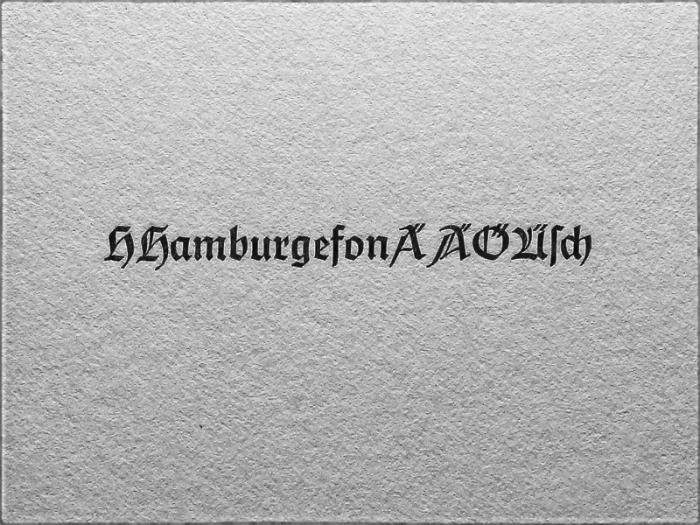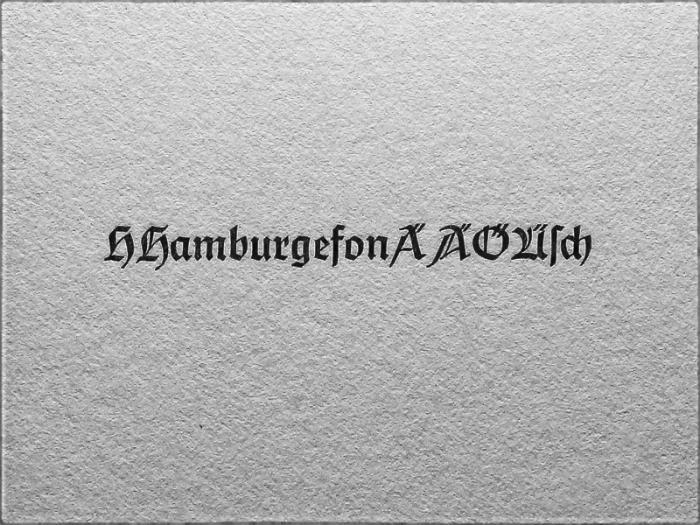
Kann mir jemand mit der Identifizierung dieser Schrift helfen? Ich habe sie in 12p Bleisatz vor etwa 10 Jahren in meine Werkstatt übernommen aus einer Setzerei-Auflösung, gußfrisch, aber ohne Namensschild. Sie ist mit Zierversalien ausgestattet. Weiß jemand, wie sie heißt?
Wieder einmal allerbesten Dank! Ich hatte die Post-Fraktur im Kapr schon vor Augen, aber sie hat in der betrachteten Ansicht deutliche Unterschiede. Im Kandler hätte ich nachschauen sollen. Die Schrift im Kapr ist wohl die digitale Version, die auch Judith Schalansky ohne Zierversalien zeigt und die vom Bleisatz doch deutlich abweicht. Deshalb dachte ich, es wäre eine andere, die ich nicht kenne. Die Digitalisierung halte ich für schlechter als die Bleisatzvariante, den verkürzten Auslauf des g, das offenere H, das breitere r – und die Zierversalien sind neu gezeichnet. Darf ich fragen, was Sie von der digitalen Interpretation halten? Und hätte man sie nicht anders nennen sollen?
Wenn die Digitalisierung so deutlich abweicht, könnte man mir eine große Freude machen, und mir eine möglichst hoch auflösende Abbildung aller Figuren zukommen lassen. Ich würde sie nämlich gern so originalgetreu wie möglich digitalisieren. Gerne auch eine Ablichtung der Lettern, da ich dann auch den Kegel sehe, und dies komplett in die Font-Metrik übernehmen könnte.
Ich hab die Schrift nur in Cicero, also 12p. Für eine Digitalisierung müßte man auch die großen Grade berücksichtigen und eine Mischung aus allem herstellen, nicht wahr? Mir fehlt die Zeit für solche Arbeiten, also alles setzen und Reproabzüge machen, das dauert ja mindestens zwei Stunden. Es müßte in Bibliotheken Kataloge der Schrift geben.
Ach, Herr Reichardt, noch eine Nachfrage: Kapr gibt 1937 und die Gießerei Stempel an, Sie nennen Berthold. Würden Sie da noch mal nachschauen?
fraktur.de sagt: Die Entstehung der Post-Fraktur, wie die Schrift später im Handel hieß, zog sich über mehrere Jahre hin und war von einigen Rückschlägen überschattet. Erst als die Schrift 1937 von der Gießerei Berthold übernommen wurde, kam es zu einem zügigen Ausbau der weiteren Grade (6-48p).
und weiter:
Entworfen von Herbert Post (1903-01-13 Mannheim bis 1978-07-09 Baiersoien) in den Jahren 1933 bis 1935
gestochen von Paul Koch
hergestellt von der Schriftgießerei Bauer in Frankfurt
übernommen von Berthold in Berlin und dort ausgebaut und vervollständigt.
Ab 1940 entstanden die Zierversalien Mager und Halbfett.
Über die bewegte Entstehungsgeschichte gibt der Katalog zur Ausstellung über das Schaffen von Herbert Post Auskunft: ISBN 3-930195-22-4 (Halle 1997), darin der Aufsatz von Katja Schneider: „Die Schriften von Herbert Post“ (Seiten 61 bis 90, mit zahlreichen Abbildungen).
Markwart Lindenthal hatte den mageren Schnitt von Gerhard Helzel erworben und benutzt ihn für die täglichen Briefe. In Ermangelung der Auszeichnungsschriften hat er mit seiner Söhne Unterstützung diese Ergänzungen selbst vektorisiert und damit die Schriftenfamilie vervollständigt.
(Post-Fraktur für die täglichen Briefe – das ist drollig. Wenn sie gut gemacht sind, bekommt der Postempfänger eine Urkunde, und wenn sie mit den langen WORD-Voreinstellungszeilen geschrieben sind, einen Haschmich.)
Ich hab die Schrift nur in Cicero, also 12p. Für eine Digitalisierung müßte man auch die großen Grade berücksichtigen und eine Mischung aus allem herstellen, nicht wahr? Mir fehlt die Zeit für solche Arbeiten, also alles setzen und Reproabzüge machen, das dauert ja mindestens zwei Stunden. Es müßte in Bibliotheken Kataloge der Schrift geben.
Wenn ich dann ein gutes Foto von allen Figuren in hoher Auflösung hätte (vielleicht mal ausprobieren, die Lettern auf den Scanner zu stellen), hhätte das allerdings auch den Vorteil, dass man dann die Schrift in der Test-Entwurfsgröße digitalisieren würde. Viele Digitalisierungen kranken ja gerade daran, das es praktisch nur die Display-Größe gibt, weil hier nach einer großen Schriftgröße digitalisiert wird, und das, weil die Abdrucke, die zur Vorlage dienen, einfach bei großen Schriftschnitten sauberer sind. Direkt von den Lettern bekäme man damit vielleich auch eine gute Textschrift, die sich dann mit der anderen Digitalisierung gut kombinieren ließe.
Es tut mir wirklich leid, mir fehlt die Zeit dafür. Ich könnte so etwas nur als Auftrag gegen Rechnung übernehmen, aber nicht kostenlos, das dauert einfach zu lange. Und ich habe auch keinen Scanner. Ist es nicht ohnehin sinnvoller, nach den Originalzeichnungen und Probegüssen zu forschen? Denn auch für den Bleisatz mußten Schriftschöpfer Kompromisse eingehen. Oder soll ich den Stezkasten fotografieren? Die Schrift ist stehend untergebracht, zufällig. Aber auch das kostet ein halbes Stündchen. Stativ, Langzeitbelichtung, Ausleuchtung. Das halbe Stündchen habe ich dieses Jahr nicht mehr. Im April vielleicht. Oder du kommst vorbei oder schickst jemanden, der ein Foto machen kann.
Nach den Originalzeichnungen zu digitalisieren ist natürlich in einer Richtung ideal - das gint dann einen super exakten Font, der allerdings dann zumeist auch für eine große Textgröße ideal ist. Auf der anderen Seite bringt die Digitalisierung der "arbeitsgröße" mit den Kompromissen, die allein schon durch den Stempelschnitt entstanden sind, auch interessant, wird das Ergebniss dann mehr an die alten Drucke heran kommen. Ich sehe es oft, das nach Original-Zeichnungen erzeugte Fonts dann in Textgröße nicht funktionieren. Andere, die dann nach Drucken einfach per Autotracing gebaut sind aber genau so wenig, da hier ein im richtigen Druck zufälliger Fehler dann jesesmal erscheint.
Die diversen Berthold Hauptproben gibt es ab 20 Euro bei vielen Antiquariaten. Hier sind auch die kompletten Zierversalien, Ligaturen und Ziffern abgedruckt. Vermutlich effektiver als Fotos machen.
20 Euro? Vielleicht für die Proben aus den Achtzigern aber nicht für eine Bleisatz-Hauptprobe.